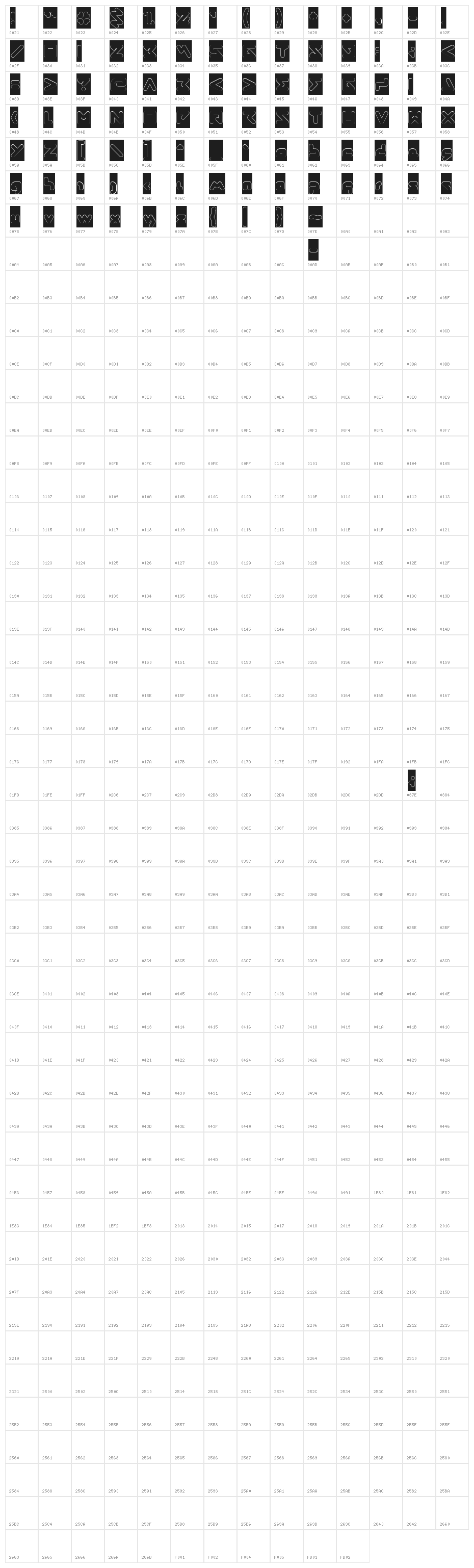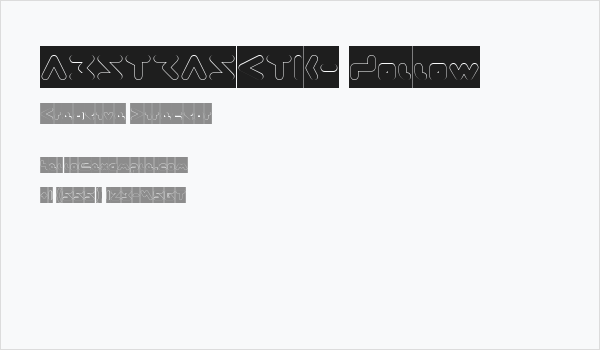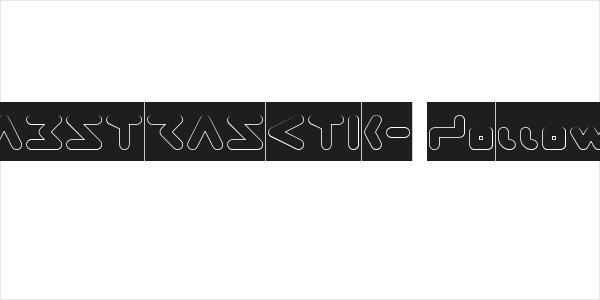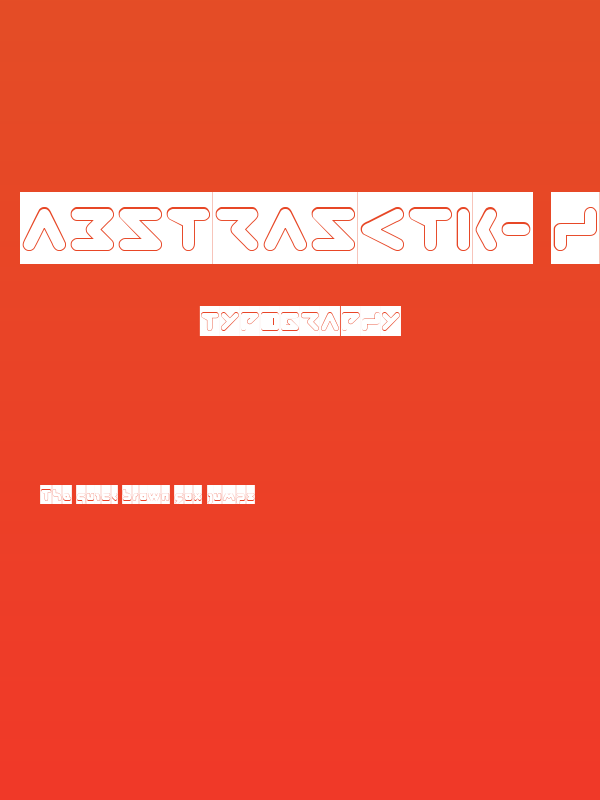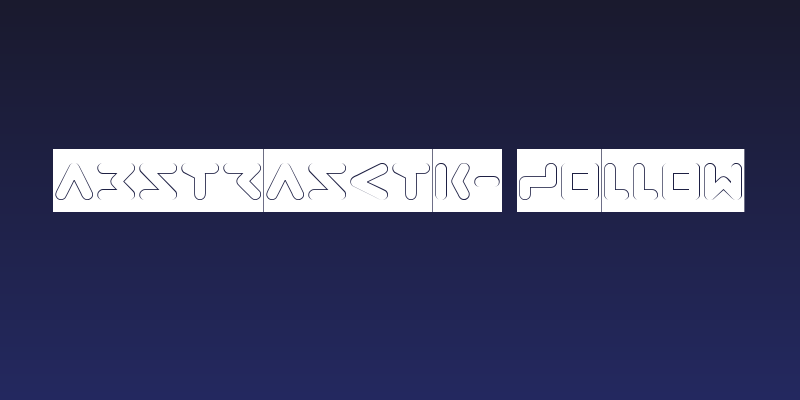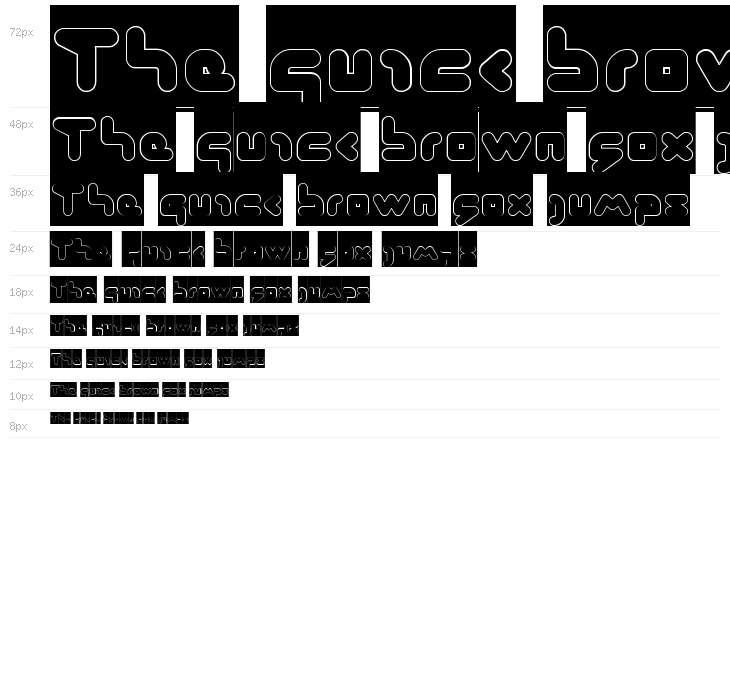
ABSTRASCTIK- Hollow Font
✎ Outline
| Progetti proposti | Ideal for sci-fi themed designs, modern posters, digital artwork, and branding that requires a futuristic touch. |